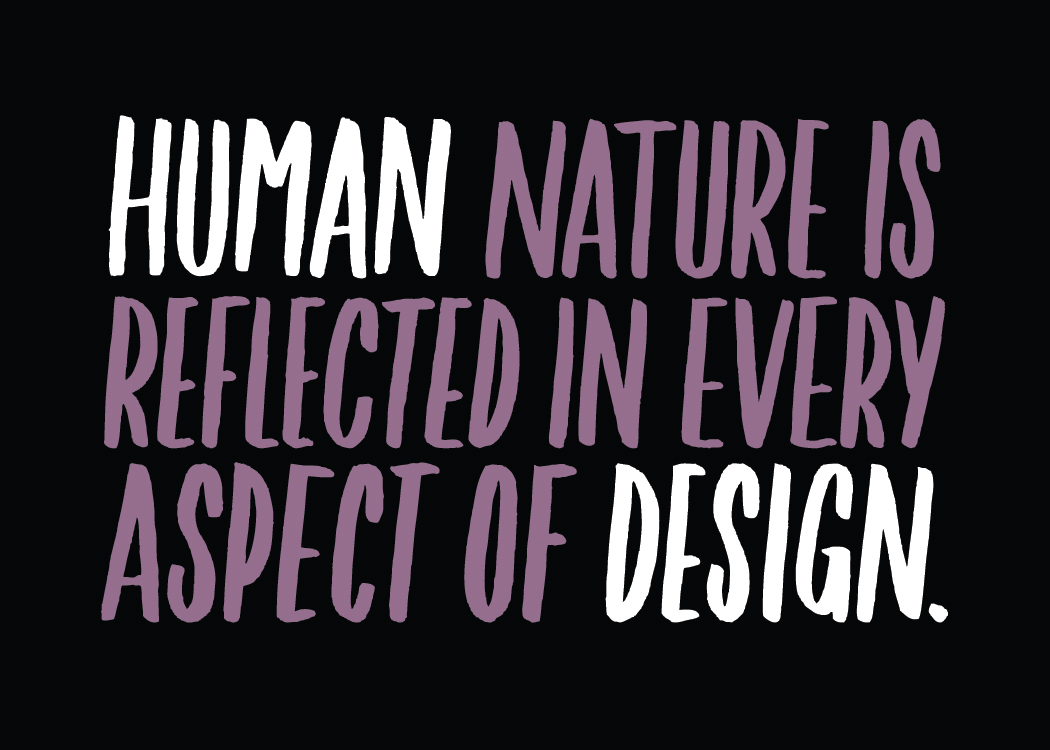
[quote]Thiết kế là truyền thông thị giác.[/quote]
Thiết kế cho phép người sử dụng tương tác với thương hiệu, sản phẩm, thông điệp hoặc ý tưởng. Nhưng làm cách nào một thiết kế lôi cuốn được chúng ta? Màu sắc? Một headline thông minh dùng một font chữ lôi cuốn? Một sự kết hợp hoàn hảo ? Thật ra, đó chính là hiệu ứng từ sự kết hợp của tất cả các yếu tố trên. Bạn có thể gọi việc kết hợp các yếu tố với nhau để tạo nên thiết kế của bạn là sắc thái hoặc cá tính.
Nhớ lại lần cuối cùng bạn thật sự đồng điệu với ai đó, một người bạn mới hoặc đồng nghiệp. Tôi đoán rằng bởi bạn bị thu hút bởi cá tính của người ấy. Thiết kế thành công nhất giống hệt như vậy: thu hút người xem bằng thêm vào cá tính, một thứ kết nối được với đối tượng mục tiêu và hỗ trợ mục đích tổng thể của thiết kế.
— Aarron Walter, Designing for Emotion (Lettering by Carolyn Sewell)
Vậy làm cách nào chúng ta đem đến sắc thái đúng đắn cho thiết kế của mình? Hãy tham khảo 3 nguyên tắc thiết kế sẽ giúp bạn bắt đầu: Màu sắc, Typography và Khoảng cách.
[quote]1 – Chạm vào cảm xúc người xem với Màu sắc[/quote]
Màu sắc là một công cụ đầy quyền lực. Khi nói đến truyền thông thị giác, chỉ một số ít công cụ có hiệu quả hơn về khả năng thu hút sự chú ý và chạm đến cảm xúc/nhận biết, điều đó làm cho màu sắc đóng vai trò rất quan trọng trong việc tạo ra sắc thái trong thiết kế của bạn. Màu sắc trợ giúp cho ngôn ngữ dễ hình tượng hơn, đó là lí do chúng ta nói “đỏ mặt tía tai” khi giận dữ hay sợ “xanh mặt”. Bởi màu sắc có liên kết đặc biệt đến cảm xúc và tâm trạng của chúng ta.
Sự liên kết đó có mặt mọi lúc bạn dùng màu trong các project, vậy nên sẽ là khôn ngoan nếu hiểu được tính tâm lý học và ý nghĩa của màu sắc. Nhưng không phải ai cũng cảm nhận về màu sắc theo một cách giống nhau. Ý nghĩa và sắc thái ta liên hệ với màu sắc khác nhau sẽ chịu ảnh hưởng bới yếu tố văn hóa và xã hội của nhóm đối tượng nhắm đến. Infographic dưới đây sẽ cho bạn thấy những nền văn hóa khác nhau sẽ định nghĩa màu sắc khác nhau như thế nào.
RESEARCH: DAVID MCCANDLESS, PEARL DOUGHTY-WHITE, ALEXIA WDOWSKI
Thử xem qua ý nghĩa của một số màu cơ bản trong văn hóa phương Tây và những thiết kế nên ứng dụng như thế nào.
Đỏ: ấm áp và giàu năng lượng
Đỏ có thể biến hóa rất nhiều ý nghĩa giao tiếp tùy vào từng bối cảnh. Vì có liện hệ tới lửa, nó có thể đại diện cho sự ấm áp hoặc nguy hiểm. Nó còn là màu của máu, nghĩa là màu đỏ đầy năng lượng và sức sống; hoặc liên hệ tới tim mạch và một số trường hợp, là bạo lực.
Tạo sắc thái: trong thiết kế và branding, đỏ làm project có sự tự tin, dũng cảm, mạnh mẽ và quan trọng là nó là màu cực kì nổi bật.
Cam: tuổi trẻ và lạc quan
Cũng là màu của lửa, màu cam hội tụ cái ấm áp của đỏ và sự phấn khởi của vàng làm nên sắc thái cho sự năng động, năng lượng và lạc quan.
Tạo sắc thái: Cam không cần làm quá nghiêm trọng. Trong design và branding, nó giúp tạo một rung động sáng tạo, trẻ trung và phong cách casual.
Màu vàng: tươi sáng và hứng khởi
Là màu của mặt trời, vàng liên hệ tới hạnh phúc, phấn khởi, tình bạn và sự tươi mới của mùa xuân. Nó cũng là dấu hiệu cuả cảnh báo trong một số trường hợp.
Tạo sắc thái: Trong thiết kế và branding, vàng thu hút sự chú ý, cũng như đỏ, nhưng với thái độ thân thiện và vui tươi hơn.
Ví dụ như tờ báo điện tử này, chọn màu vàng chanh và biểu tượng minh họa thân thiện hợp với những thông tin tích cực, tốt đẹp.
Màu xanh lá: tươi mới và thiên nhiên
Đây là màu của thiên nhiên, cây cối và sinh trưởng. Vì thế nó liên hệ đến sức khỏe, sự tươi ngon và tính chất “tự nhiên 100%”. Xanh lá ở tone tối hơn đại diện cho giàu có ( bất cứ gì liên quan đến tiền) và ổn định, như logo đại diện dưới đây.
Tạo sắc thái : Trong thiết kế và branding, màu sắc liên hệ đến thiên nhiên như xanh lá và nâu thường dùng cho những việc kinh doanh công nghệ xanh ( các tính chất tự nhiên, sức khỏe, bền vững, thân thiện vs môi trường, hữu cơ, v..v..)
Xanh dương: Ổn định và tin tưởng
Màu của biển và bầu trời, xanh dương liên hệ đến hòa bình, trong sạch. Đối nghịch với các màu nóng khác đầy nhiệt huyết, xanh luôn tạo cảm giác bình yên.
Tạo sắc thái: trong thiết kế và branding, xanh dương dùng rộng rãi và là một trong những màu linh hoạt nhất. Nó liên hệ với sự tin tưởng, an toàn và ổn định. Xanh đậm hay xanh navy là lựa chọn phổ biến cho các bối cảnh doanh nghiệp vì nó tạo cảm giác chuyên nghiệp và nhanh gọn.
Tím/Violet: Sang trọng và bí ẩn
Màu tím từ lâu được gắn với hoàng gia, uy quyền và danh dự. Nó còn có tính huyền bí hoặc liên quan đến tôn giáo.
Tạo sắc thái: Trong thiết kế và branding, màu tím đậm vẫn là biểu tượng cho sự sang trọng hoặc giàu sang, trong khi tone nhạt hơn biểu trưng cho sự nữ tính hoặc thân thiện với trẻ em.
Bao bì dành cho sản phòng thủ công này thể hiện chất lượng cao cấp của sản phẩm với sự kết hợp của vàng kim và tím.
Đen: hiện đại và tinh tế
Giống như màu đỏ, đen có rất nhiều ý nghĩa. Nó có thể đại diện cho quyền lực, sang trọng, tinh tế, và độc đáo. Mặc khác, nó là biểu tượng của cái chết, độc ác hoặc huyền bí. Trong thời trang, đen là màu của sự trang trọng ( trong làm việc) hoặc thương tiếc ( đám tang ).
Cảm xúc còn có thể điểu khiển cách người khác giao tiếp với thiết kế của bạn. Vậy chúng tôi hy vọng những kĩ thuật và ví dụ này có thể cho bạn vài ý tưởng để tích hợp săc thái vào những project của bạn và đạt hiệu quả giao tiếp cao hơn. Chúc bạn làm việc vui vẻ!